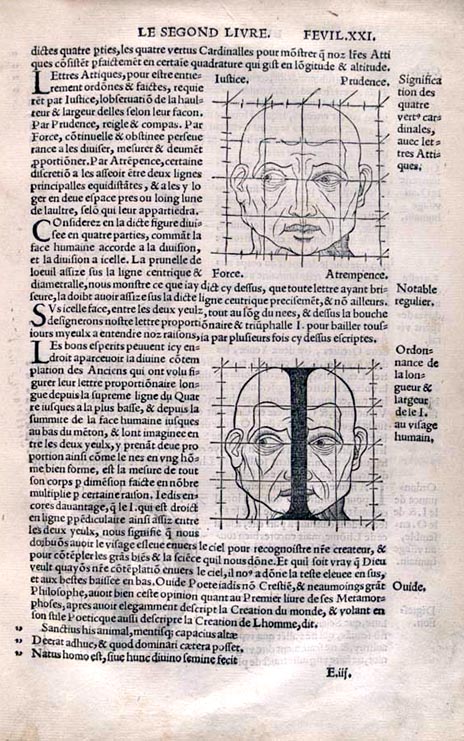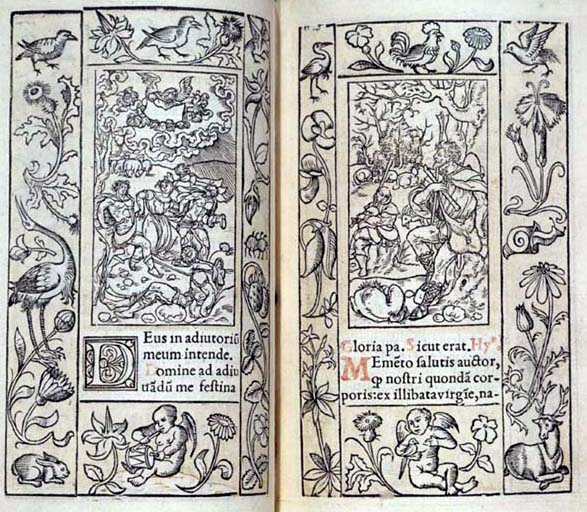
Geofroy Tory(Bourges, 1480 - Paris, 1533). Tipógrafo em Paris, teve uma participação destacada na transição operada em França, que substituiu os tipos góticos pelos tipos humanísticos: a letra renascentista.Este humanista francês foi professor de literatura grega, latina e hebraica, corrector, livreiro e imprimeur du roi. Em França, Tory é conhecido pelas suas contribuições para a ortografia, pois introduziu as vogais acentuadas, a cedilha e o apóstrofe. Nascido em 1480, Geofroy Tory iniciou os seus estudos na Universidade de Bourges, para depois continuá-los em Roma e Bolonha com Filippo Beroaldo. Este contacto com o Humanismo italiano marcou a sua futura trajectória. Em 1523, Tory alugou uma oficina em Paris, na Rue St. Jacques, para aí começar a sua actividade como libraire. Em 1524 editou a obra Gotofredi Torini Biturici In filia Chariss. Virguncularum elegantiss epithapia & dialogi, livro onde aparece o famoso borde que repete no seu primeiro Livro de Horas, impresso em 1525 por Simon de Colines.
Champfleury: Lart & Science de la deue & vraye Proportion des Lettres AttiquesTambém em 1524, Tory começou a redacção de um curioso e bizarro livro, que foi impresso (provavelmente por Gilles Gourmont) em 1529: Champfleury: Auquel est contenu Lart & Science de la deue & vraye Proportion des Lettres Attiques, quon dit autrement Lettres Antiques, & vulgairement Lettres Romaines proportionnées selon le Corps & Visage humain.
Tory quiz fundamentar as formas das letras nos traços do rosto e da anatomia humana e deu-nos descrições antropormóficas, mescladas de obscuro simbolismo, plenas de piruetas intelectuais. O lado prático da sua obra: as suas letras vêm
inscritas numa grelha de 10 x 10 pequenos quadrados. Tory era conhecedor da
obra Divine Proporpione, cuja estética criticou em várias
partes. Também citou «O trabalho de Geoffrey Tory, proeminente tipógrafo francês do princípio do século XVI, incorporou uma síntese cosmológica própria dos eruditos do Renascimento. Tory usou os seus estudos das letras como o meio para integrar o conhecimento clássico e místico, inspirado no simbolismo Neo-Pitagórico e Neo-Platónico. Por exemplo, Tory utilizou a teoria das proporções derivadas da figura humana como a base dos seus desenhos, mapeando o corpo humano numa grelha sobre a qual ele baseou as suas maiúsculas uma ideia característica do primeiro Renascimento e puramente humanista.» [Drucker, Johanna. The alphabetic labyrinth, London, Thames and Hudson, 1999, p.164]